제안서나 기획서 작성에 고민 많은 여러분, 그거 아시나요? 폰트 하나만 바꿔도 일잘러처럼 보일 수 있다는 사실! 보기 좋은 떡이 먹기도 좋다잖아요. 산돌구름이 성공적인 기획서 및 제안서에 사용하기 좋은 폰트 4종을 모아봤습니다. 편안하면서도 강조하고 싶은 내용을 잘 드러낼 수 있다는 점이 특징이에요.
1. 한글씨 / HG인문고딕
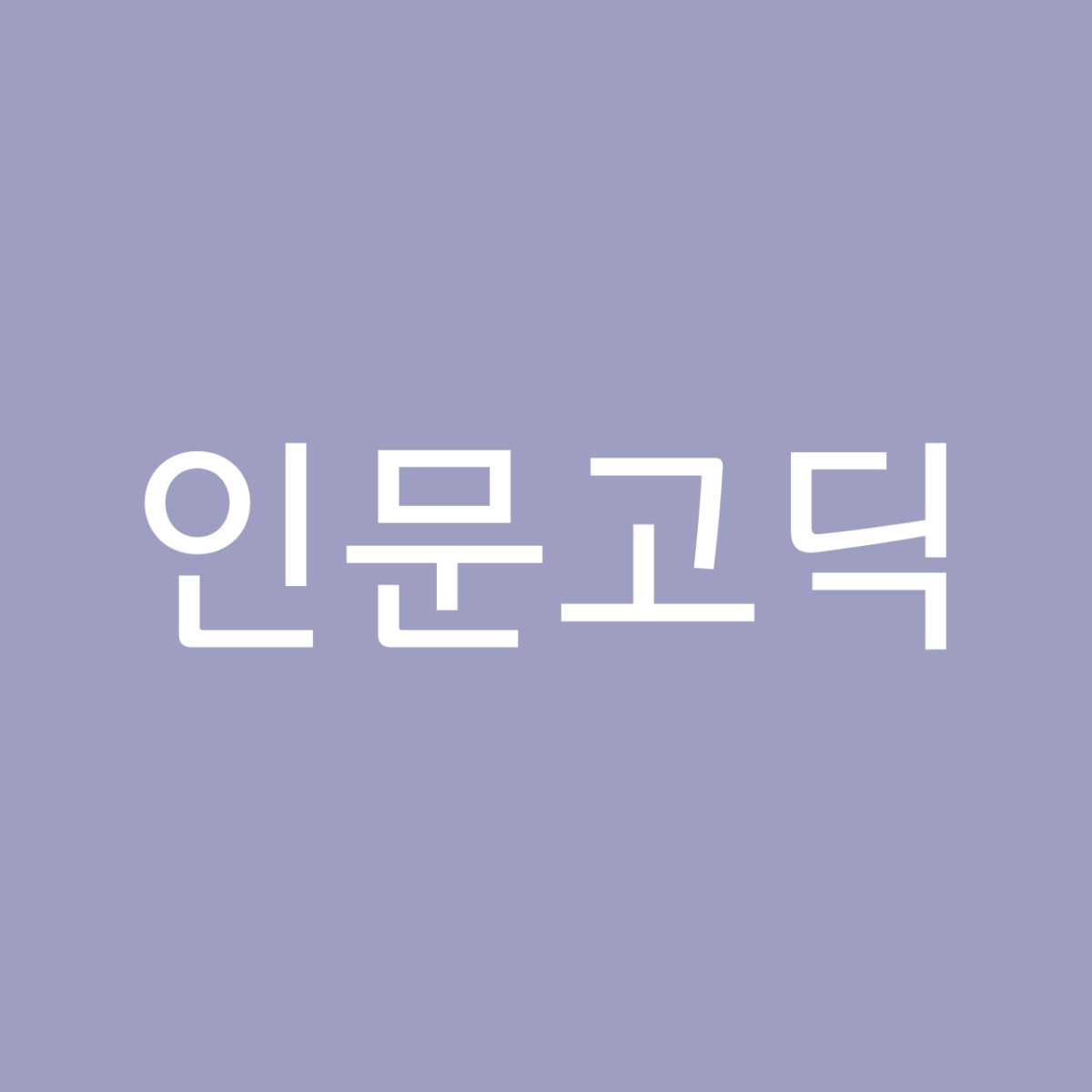
HG인문고딕은 새로운 본문용 한글 고딕 서체를 기획한 폰트로, 고딕이지만 손글씨적인 특징이 있어 기존의 고딕과 차별화되는 폰트입니다. 자소의 형태에 곡선이 반영되어 부드러운 인상을 주기 때문에 딱딱하지 않은 분위기의 제안서를 작성해야 할 때 HG인문고딕을 추천해 드려요. 총 10가지 웨이트의 풍부한 패밀리로 구성되어 있어 용도에 맞게 사용할 수 있으며, 1만1172자 한글을 모두 표현할 수 있어 원하는 용처 어디든 편리하게 사용해보세요.
2. 위폰트 / 인텔리산스엣지
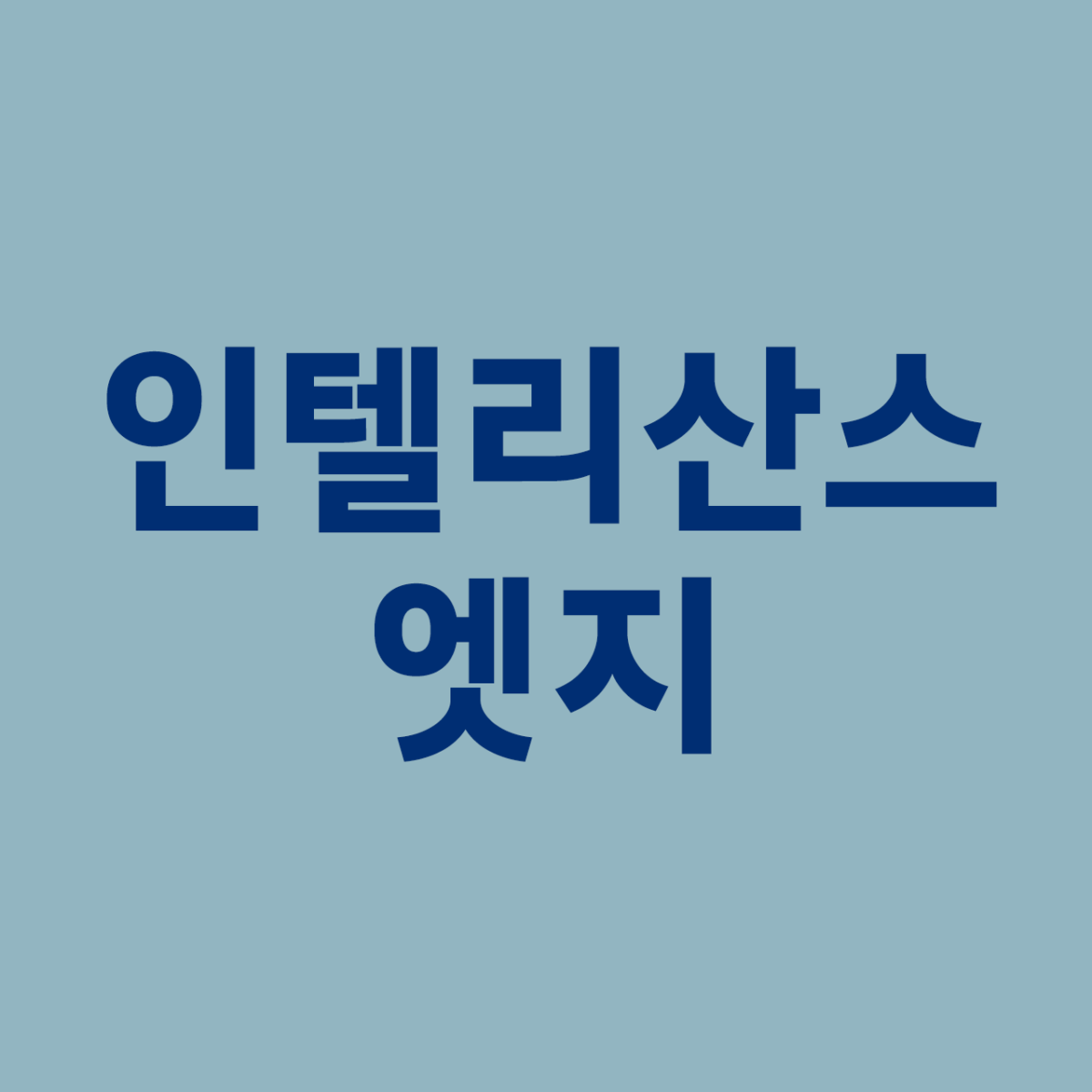
인텔리산스엣지는 ‘모두를 위한 전용서체’라는 콘셉트로 만들어진 고딕 스타일의 본문/제목 겸용 폰트입니다. 비례와 균형이 맞게 정교하게 다듬어진 인텔리산스엣지는 어떤 회사의 이미지와도 엣지 있게 어우러지며 신뢰도를 높여주는 인상을 선사합니다. 산돌구름에서는 라이선스 제한 없이 폰트를 자유롭게 사용할 수 있기 때문에, 기업의 CI/BI에 활용하시는 것도 가능합니다. 총 10가지 두께로 원하는 용도와 매체에 따라 폭넓게 선택해서 사용할 수 있는 인텔리산스엣지, 그리고 둥근 버전의 인텔리산스라운드까지 만나보세요.
3. 로올타입 / 오흐탕크 한글 텍스트
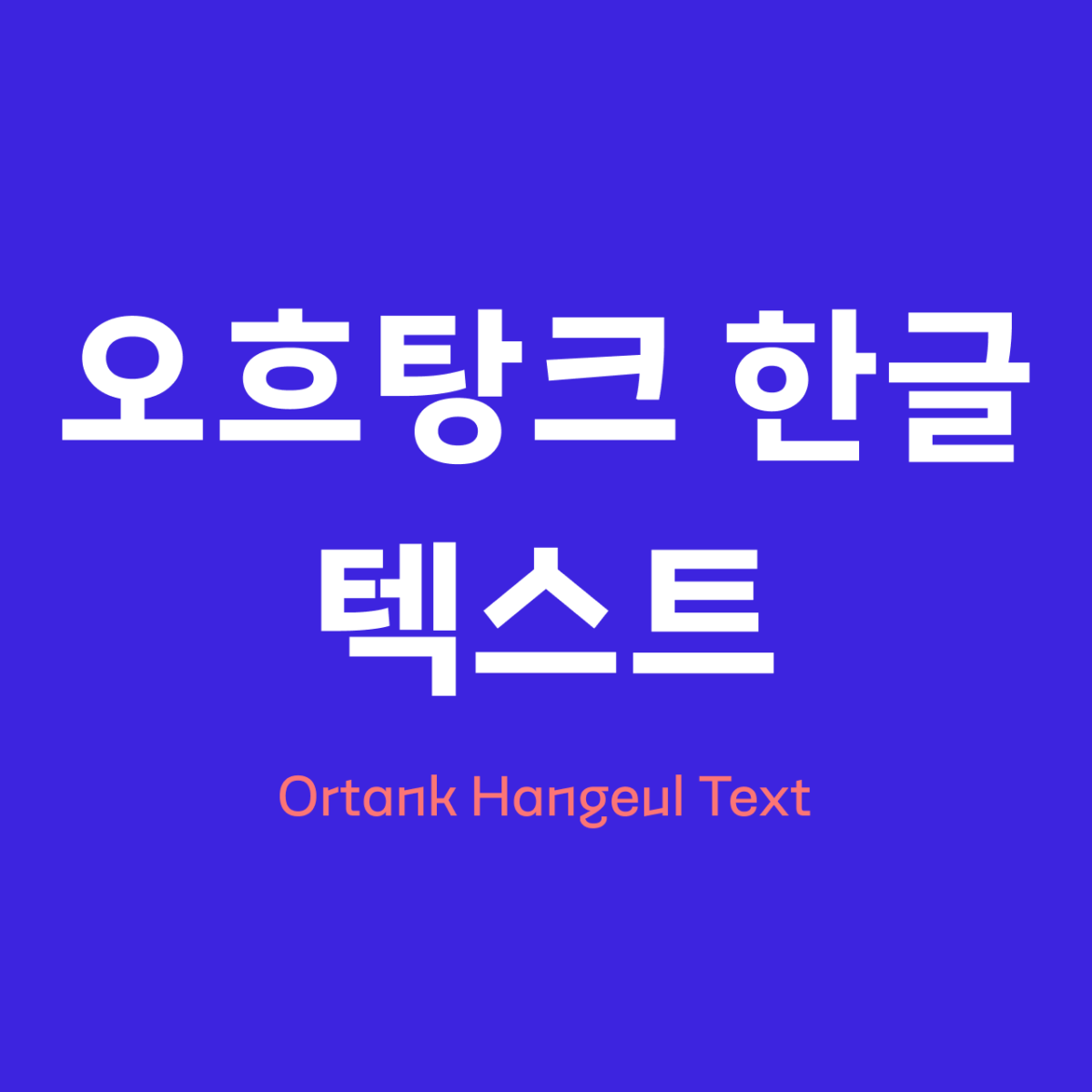
오흐탕크 한글 텍스트/디스플레이 폰트는 기하학적이면서 디지털적인 느낌을 주도록 고안된 폰트입니다. 직선형 스타일에서 오는 고전적인 느낌에 단순함을 결합시켜, 기계적인 아이템 또는 웹 기반의 문서와 잘 어우러지는 폰트로 추천합니다. 어느 크기에서든 가독성을 높게 유지할 수 있도록 제작되어 큰 단락뿐만 아니라 작은 텍스트까지 여러 종류의 콘텐츠에서 사용 가능하고, 동일한 구조이지만 더 독특한 형태로 제작된 ‘오흐탕크 한글 디스플레이’까지 함께 사용하면 독창성을 높일 수 있습니다. 총 9종의 굵기로 구성된 오흐탕크 한글 텍스트로 감각적인 제안서를 완성해 보세요!
4. 브래너스 / Priego
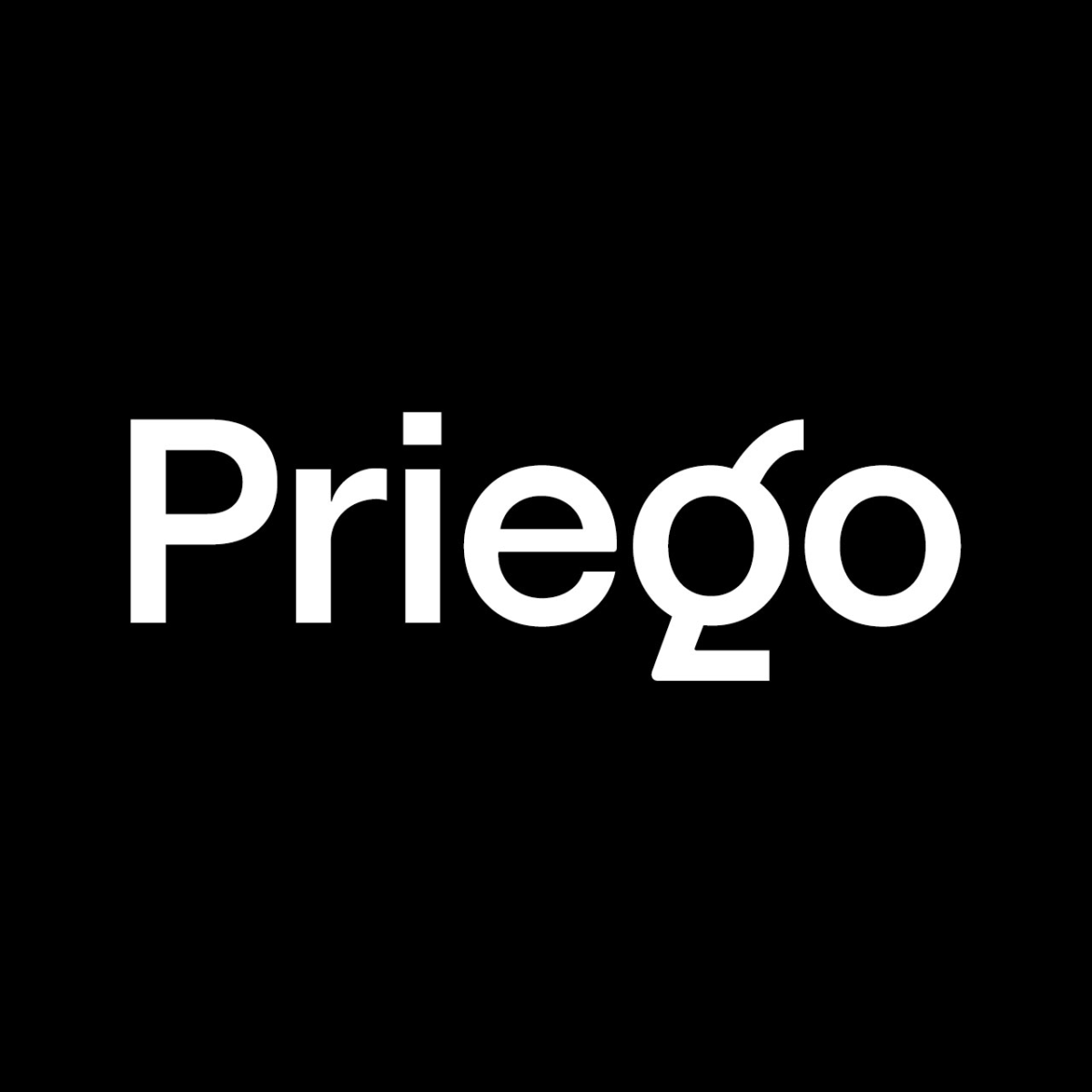
제안서를 작성할 때 영문 폰트를 고르는 것도 고민이 많이 되는 부분인데요. 그 부분을 해소시켜줄 수 있는 브래너스의 라틴 폰트를 소개합니다. Priego는 안정적인 균형감과 가독성을 겸비한 모던 그로테스크 디자인을 위한 폰트입니다. 헤드라인, 로고, 브랜딩뿐만 아니라 본문 및 일반 텍스트 영역까지 커버할 수 있으며 무려 18종의 웨이트로 구성되어 있어 폰트 하나만으로 작업물을 완성할 수 있습니다. 맑은 고딕, Sandoll 고딕 Neo 등 기본적인 한글 폰트와 함께 개성 있는 영문 폰트를 사용하고 싶다면 Priego로 작업을 시도해 보세요!